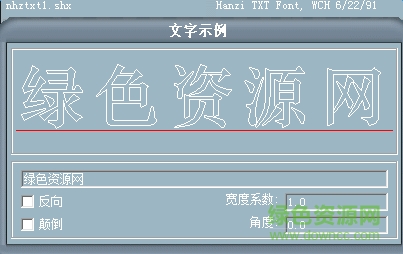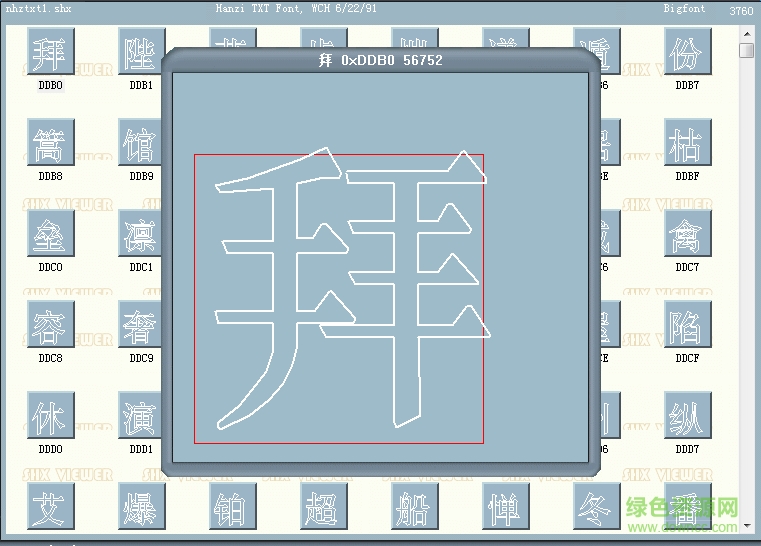
nhztxt1字體是一款cad系列空心字體軟件,此字體大方得體,十分優(yōu)美好看,為解決部分cad圖紙亂碼現(xiàn)像,有需要就來綠色資源網(wǎng)下載使用吧,更多cad字體免費下載!
nhztxt1.shx是autocad中的常用字體,支持中英文輸入,字跡構造簡約大氣,安裝簡單方便,如果你想讓你的文字閱讀更舒適更簡潔,可以來本站免費使用哦!